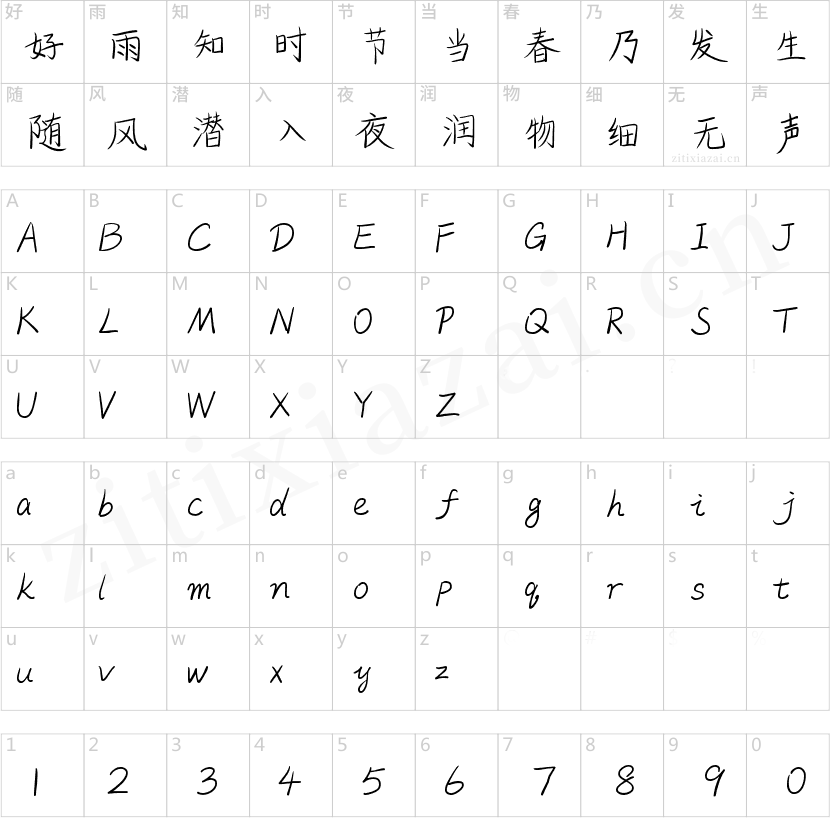
字魂75号-柳叶竹眉体
字魂75号-柳叶竹眉体,这款字体结构工整、笔画清晰,兼顾美观与易读性,适用于标题、正文、海报、包装、LOGO 等多种场景。字形优雅稳定,风格百搭耐看,适配日常排版与创意设计,让文字呈现更舒适、更具质感。字魂75号-柳叶竹眉体一笔一画,皆是细节,以均衡的比例、流畅的线条打造舒适视觉体验,字形端正大气,风格简约现代。无论是商业设计、品牌宣传还是日常排版,都能轻松驾驭,让文字更有格调与力量。字魂75号-柳叶竹眉体字体下载。
字魂字体字小魂柳叶竹眉体字体是由字魂创意字库设计并生产的一款可商用的字体,被收录于字小魂系列。该字体支持GB-2312标准,包含6763个中文、字母、符号和数字,字体类型偏向硬笔手写,具有简约、时尚的风格,在市面上广泛用于视频综艺、印刷品&包装、社交等场景。